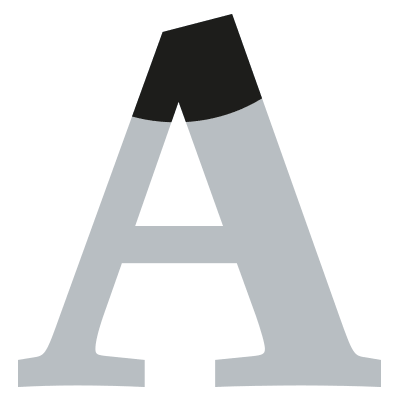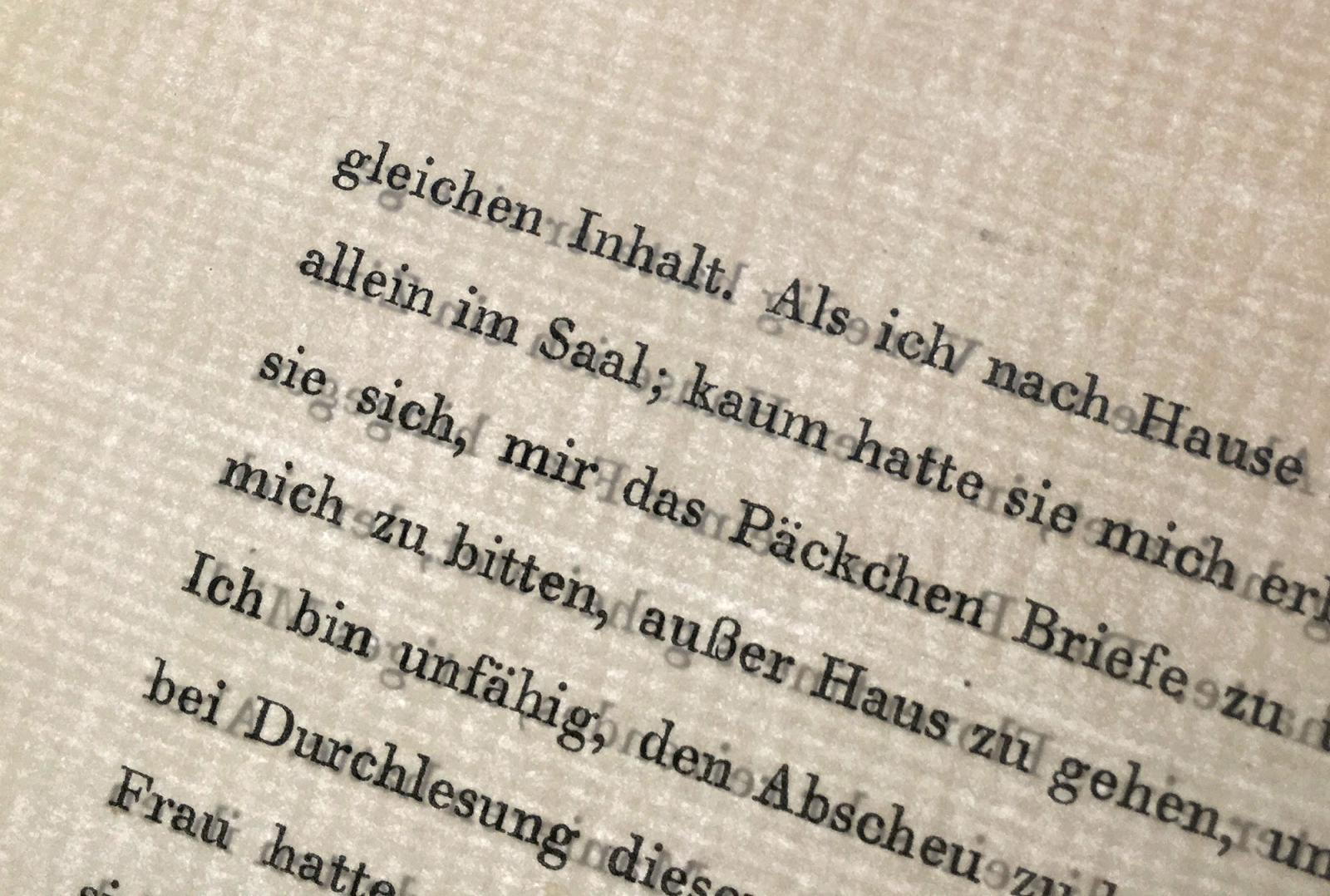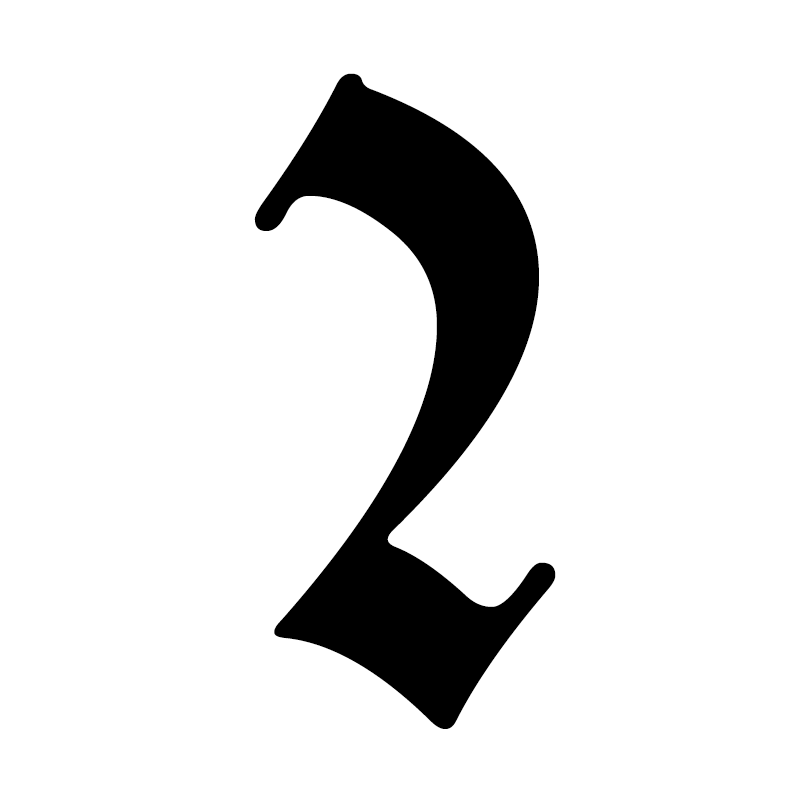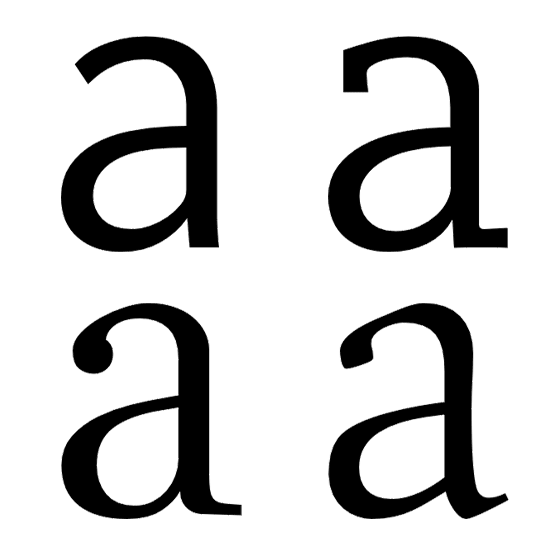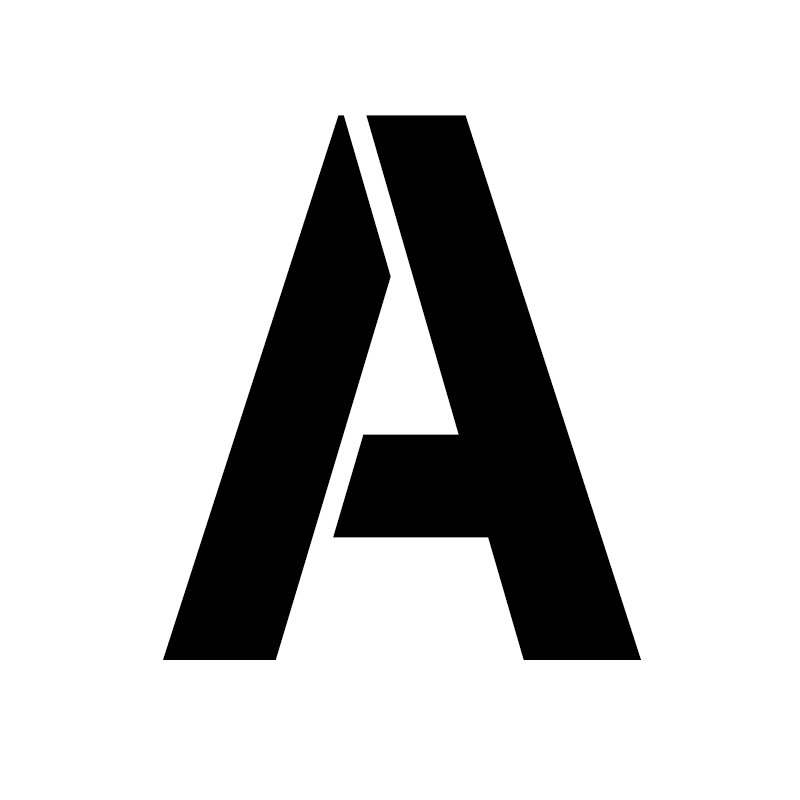
Verantwortlich für den Entwurf zeichnete ein vierköpfiges wissenschaftliches Komitee. Zur Planung entstand zunächst ein völlig neues Punktsystem, das später von Fournier und Didot übernommen und verfeinert wurde. Die Zeichnungen für die aufrechte Romain du Roi erfolgten durch Konstruktion in einem Rastersystem von 48×48 Einheiten. Die Zeichnungen wurden dann in Kupfer gestochen und dienten dem Stempelschneider Grandjean als Vorlage für den Schnitt der Lettern. Die mathematische Konstruktion der Entwürfe war zu dieser Zeit etwas völlig Neues, auch wenn sich deren Stringenz nicht vollends bis in den Stempelschnitt erhielt. Es gab nun keine gekehlten Stämme mehr, sondern absolut gerade Linien – ein Gestaltungselement, das bei den klassizistischen Schriften später übernommen wird. Leicht zu erkennen ist die Schrift außerdem am Kleinbuchstaben l, der an der linken Seite einen ungewöhnlichen Sporn hat.
1702 wurde die Schrift erstmals für das Buch »Médailles sur les Principaux Evènements de la Regne de Louis le Grand« eingesetzt. Vollendet wurde die Romain du Roi jedoch erst 1745. Auch wenn die Romain du Roi nur für die köngliche Druckerei bestimmt war, nahmen sich andere Schriftgießer — etwa Pierre Simon Fournier — ein Beispiel an diesem Stil und führten diese Entwicklung fort. In Verlaufe des 18. Jahrhunderts breitete sich der Stil dann über ganz Europa aus und um 1800 erreichte die klassizistische Typografie mit ähnlich konstruiert wirkenden Schriften dann ihre volle Blüte.
Das runde r kann in Fonts als grafische Variante über OpenType oder über den Unicode-Wert hinterlegt werden. Aus Kompatibilitätsgründen wurde auch eine Großbuchstabenvariante definiert:
Großbuchstabe: U+A75A latin capital letter r rotunda (Ꝛ) Kleinbuchstabe: U+A75B latin small letter r rotunda (ꝛ)
Der typische Stil dieser Schablonenschriften wird aber bei digitalen Schriften auch teilweise als rein stilistisches Merkmal eingesetzt und die Erstellung von Schablonen ist dann nicht immer zwingend möglich.
Hans Peter Willberg schreibt im Buch »Fraktur« (Hermann Schmidt Verlag Mainz, 1993), dass »der Setzervolksmund« schon in den 1930er-Jahren von Schaftstiefelgrotesk sprach. Es gibt allerdings keine weiteren Quellen, die dies unterstützen.
Aus einer Werbeanzeige zur Tannenberg
Bei der Einordnung von Schriften in Systeme zur Schriftklassifikation ist die Schattenachse ein wichtiges Kriterium, da sie ein typisches Merkmal verschiedener Schriftepochen darstellt.
Als komplettes Möbelstück in größeren Druckereien war gegebenenfalls auch die Bezeichnung Metteurtisch (»composing/imposing table«) in Verwendung.
Stilgruppen
Dynamisch (humanistisches Formprinzip)
Statisch (klassizistisches Formprinzip)
Geometrisch (konstruierte Form)
Dekorativ
Provozierend
Form-Gruppen
Antiqua (Strichstärkenkontrast, Serifen)
Antiqua-Varianten (Strichstärkenkontrast, keine Serifen)
Grotesk (wenig/kein Strichstärkenkontrast, keine Serifen)
Egyptienne (wenig/kein Strichstärkenkontrast, kräftige Serifen)
Schreibschriften
Fremde Schriften (Non Latin, zum Beispiel Kyrillisch)
In der Kombination dieser beiden Eigenschaften lassen sich viele Schriften gut klassifizieren. Die Bembo ist beispielsweise eine »dynamische Antiqua«; die Bodoni dagegen eine »statische Antiqua«.
Entwickelt um 1470 vor allem durch Nicolaus Jenson, Venedig, aus der humanistischen Minuskel. Das handschriftliche Vorbild dieser Druckschrift wurde mit der schräg angeschnittenen Breitfeder im Wechselzug geschrieben.
Erkennungsmerkmale:
Serifen Achse der Rundungen Ansatz (Dachansatz) der Serifen Querstrich des kleinen »e« der Kleinbuchstaben sind höher als die Versalien Strichstärken-Unterschiede Bekannte Vertreter:
Berkeley Old Style, Centaur, Deepdene, Horley Old Style, Kennerley Old Style, Trajanus, Schneidler-Mediaeval, Seneca
Gruppe II: Französische Renaissance-Antiqua
Entwickelt um 1540 vor allem durch den Franzosen Claude Garamond aus der humanistischen Minuskel. Alte Bezeichnung: Mediäval. Vorbild für die Großbuchstaben war die römische Kapitalschrift (Capitalis Quadrata) und für die Kleinbuchstaben die karolingischen Minuskel.
Erkennungsmerkmale:
Serifen Achse der Rundungen Ansatz (Dachansatz) der Serifen beim e liegt waagrecht der Kleinbuchstaben sind höher als die Versalien Bekannte Vertreter:
Garamond, Aldus-Buchschrift, Bembo, Berling, Diethelm-Antiqua, Goudy, Palatino, Sabon-Antiqua, Trump-Mediäval, Weiß-Antiqua
Gruppe III: Barock-Antiqua
Höhepunkt ihrer Blütezeit um 1750. Alte Bezeichnungen: Vorklassizistische Antiqua, Halbmediäval. Die Merkmale des Kupferstichs treten stärker hervor (Übergangs-Antiqua). Der Federduktus geht langsam verloren.
Erkennungsmerkmale:
abgerundete Serifen der Rundungen fast senkrecht Strichstärken-Unterschiede Bekannte Vertreter:
Baskerville, Caslon, Imprimatur, Janson-Antiqua, Poppl-Antiqua, Tiffany, Times-Antiqua